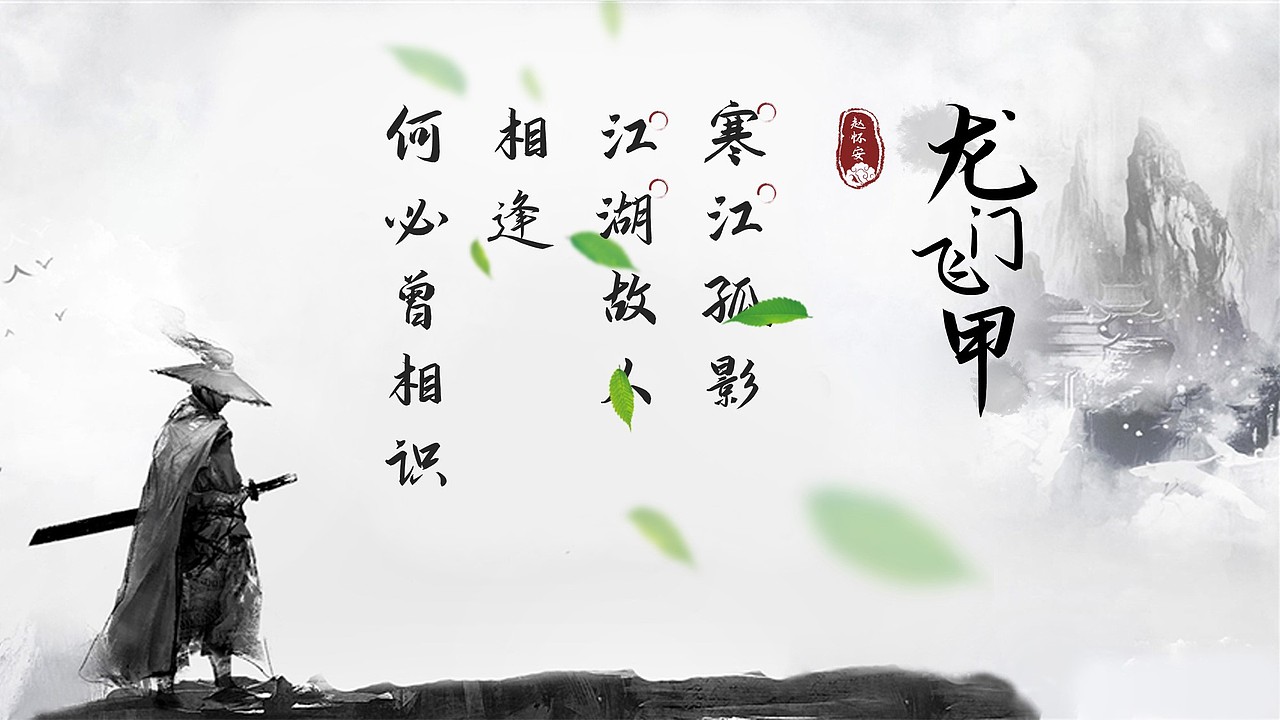
来了!我们联合推出的第二款免费字体~演示悠然小楷
演示悠然小楷是由keynote研究所和秋叶联合发布的第二款字体,献给全社会永久免费使用,包括商用。你可以在附件处下载字体包。
见过很多大开大合的书法字体后,再见悠然小楷,可能没有很惊艳之感。但艳丽与喧嚣并不一定代表力量,沉劲入骨更难能可贵。细品,却会发现悠然小楷中透着质朴、率真的气息,并在娟秀中,沉积着力量。